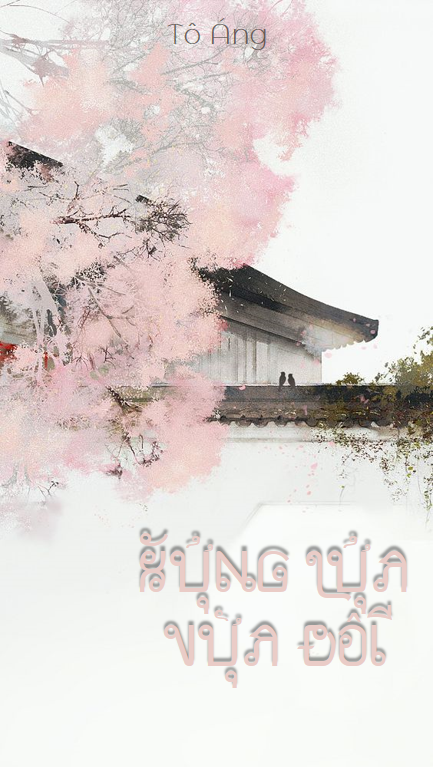
[Font] DVF Siam
Font này mình thấy khá lạ, nom vui vui, mấy người trong Makani font như theo style Thailand =))))) Theo mình thì nó hợp với đơn cổ trang, mình nghĩ vậy hoi =))))) Chứ nó xênh thật =))))))) Tiện thể pr cho truyện này, truyện này dễ thương lắm =))